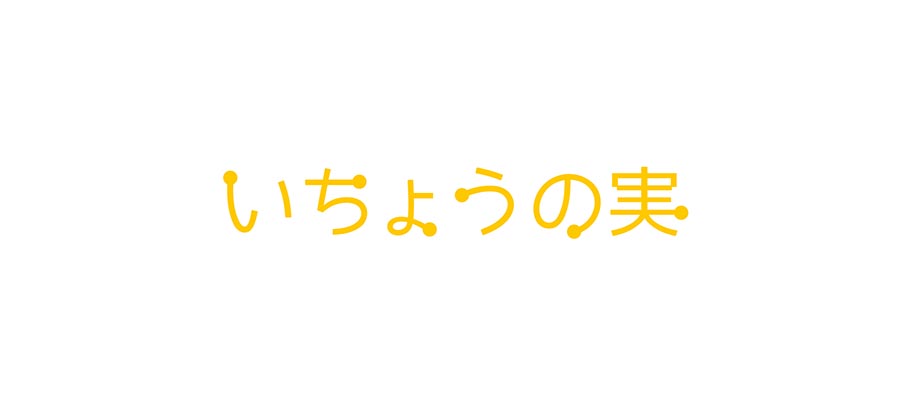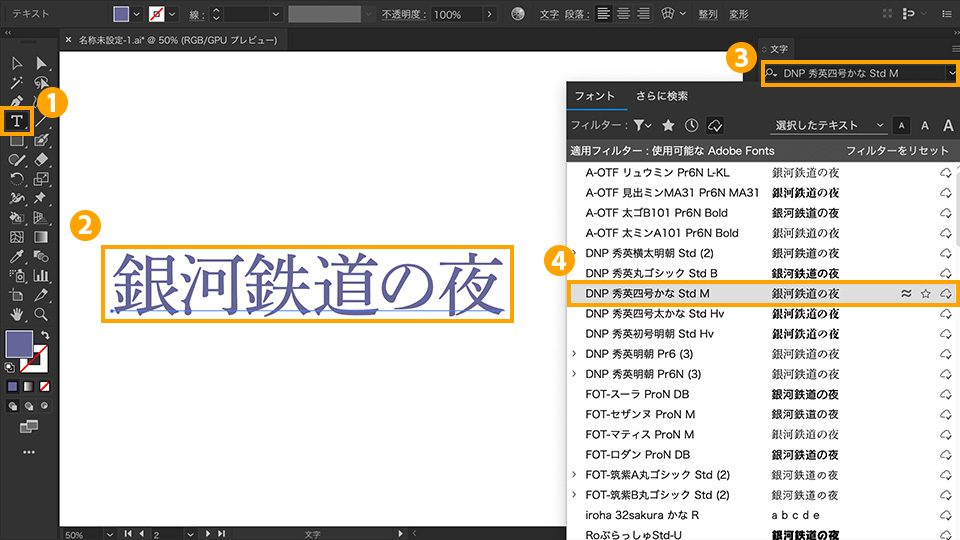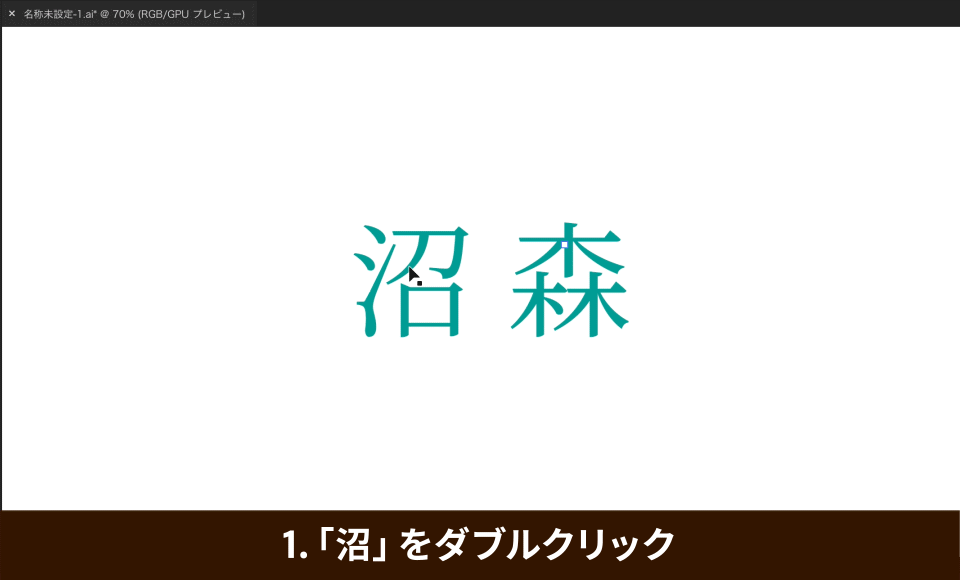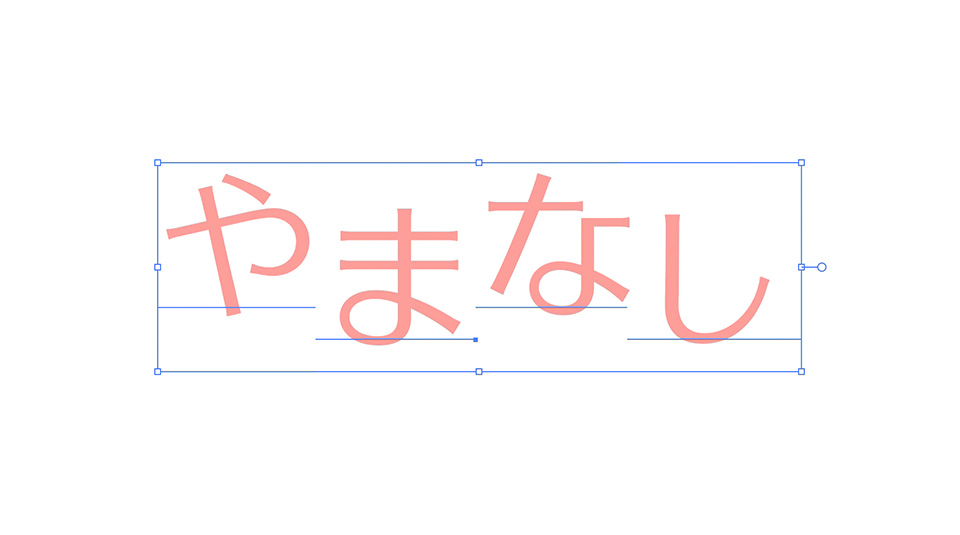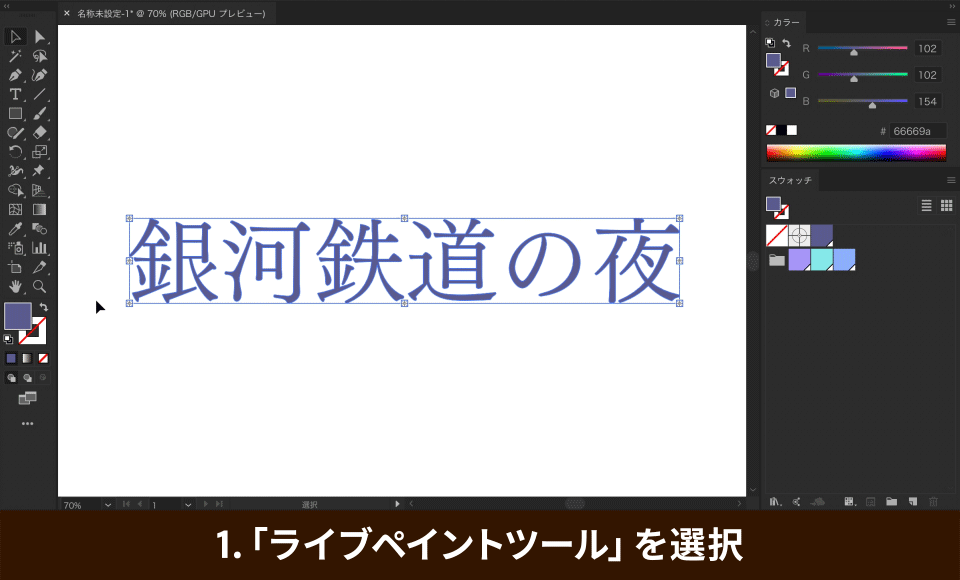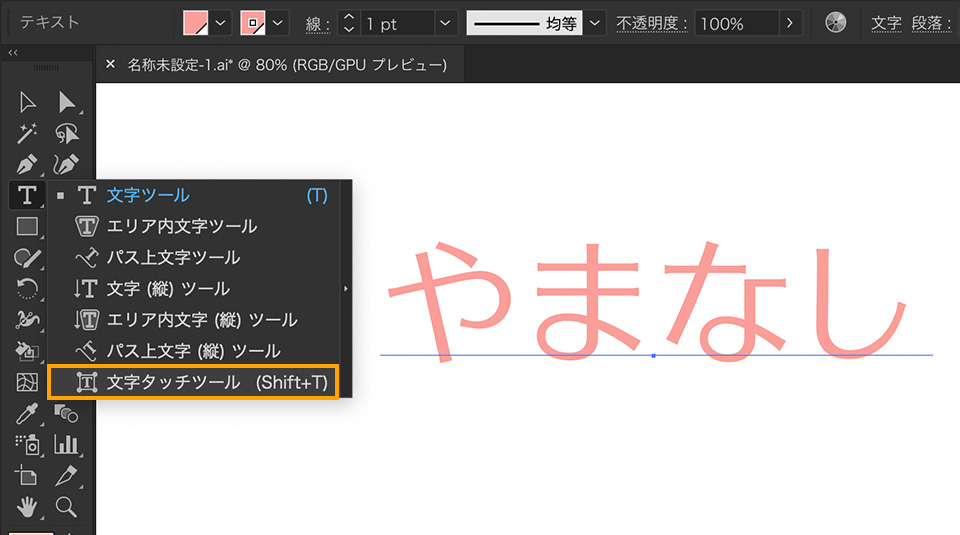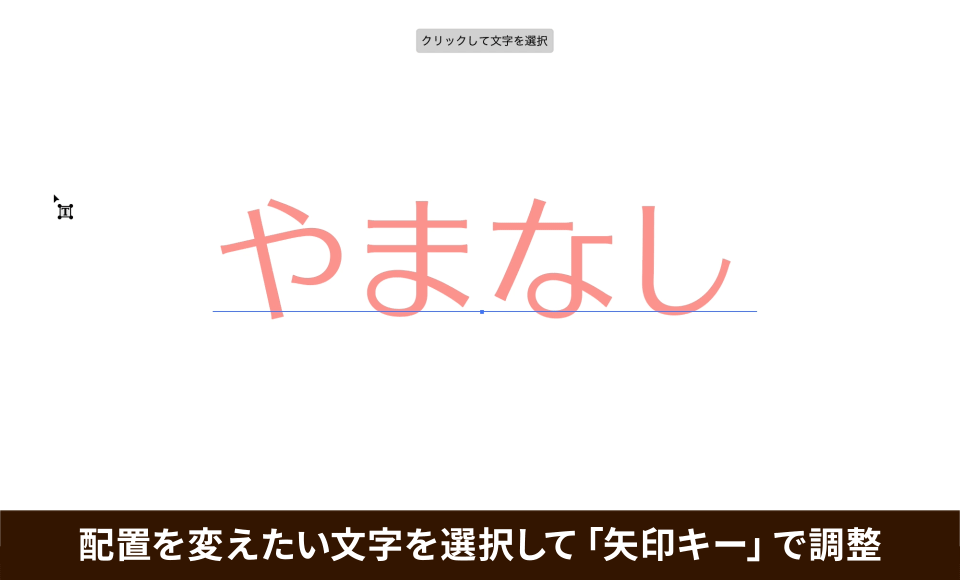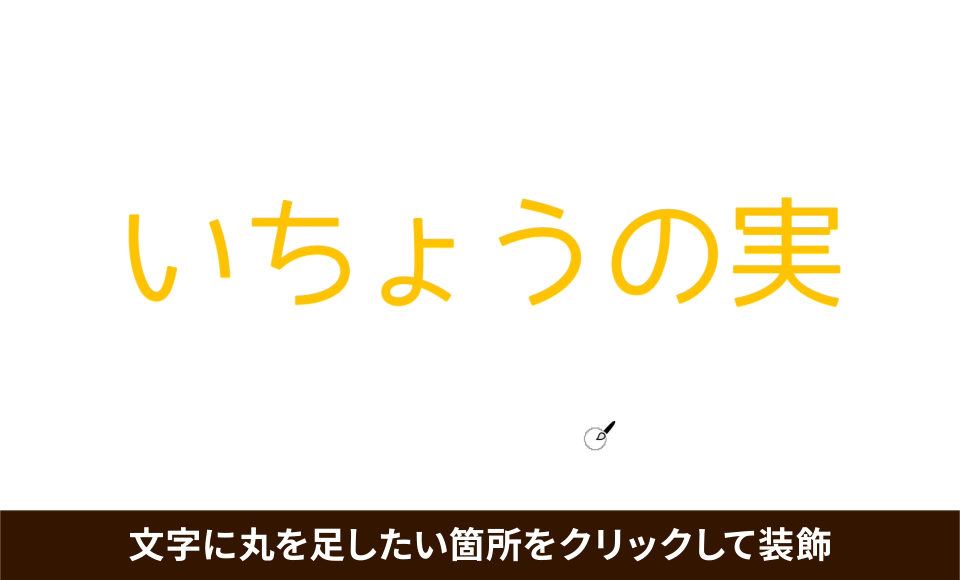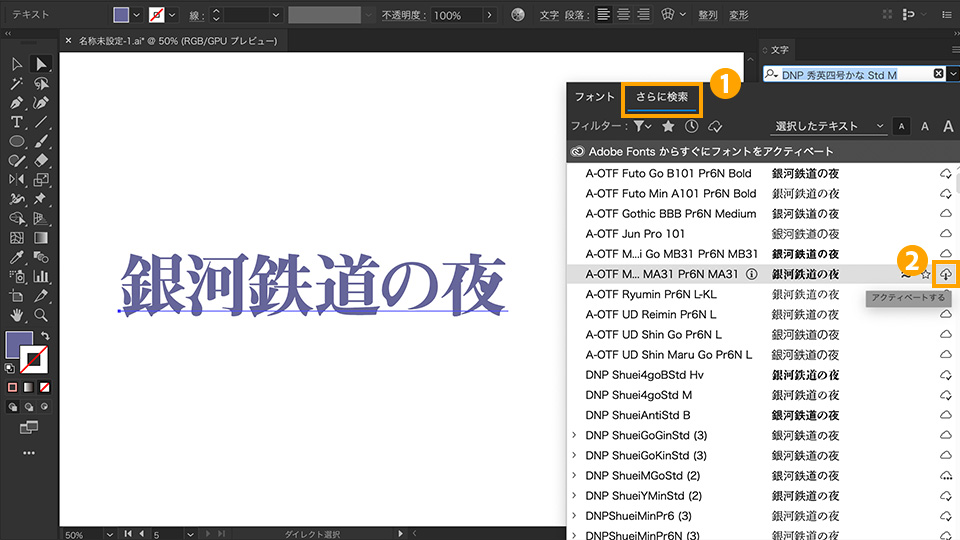
目を引くタイトル・ロゴデザインの方法:初級編
日本語のタイトルやロゴをデザインするときにヒントとなりそうなアイデアと作り方を6個紹介します。いつものフォントで入力した文字にひと手間加えて、楽しくてインパクトのあるタイトル文字を作りましょう
1. マドの中を塗る
1-1.
「文字ツール(T)」①を選択し、アートボード上をクリックして「銀河鉄道の夜」というテキストを作成します②。
1-2.
入力した文字を選択した状態で、「文字パネル」(ウインドウ → 書式 → 文字)を開きます。検索ボックス⓷の右にある「v」をクリックし、プルダウンのフォントメニュー④から使用したいフォントを選びます。
ヒント:
1-3.
文字を個別のオブジェクトとして編集するため、パスデータに変換します。これをアウトライン化と言います。「選択ツール」で文字を選択し、「書式 」→ 「アウトラインを作成」をクリックします。
文字をアウトライン化すると、テキスト情報が破棄されるため、フォントの変更や文字の打ち替えはできなくなります。
1-4.
続いて、文字のマドに色を追加していきますが、まず使用するカラーをスウォッチとして登録します。「スウォッチパネル」(ウインドウ → スウォッチ)を開き、下部の「新規スウォッチ」ボタンをクリックします。「新規スウォッチ」パネルが開くので、数値を入力してカラーを指定し、「OK」をクリックします。カラーがスウォッチパネルに追加されたら、同じ手順で計3つのカラースウォッチを作成します。
作成した3つカラースウォッチをすべて選択し、パネル下部の「新規カラーグループ」ボタンをクリックします。名前を入力し、「OK」をクリックします。スウォッチパネルに3つのカラーを含むカラーグループが追加されました。
1-5.
アウトラインテキストを選択した状態で、「オブジェクト」→「ライブペイント」→「作成」をクリックします。これでアウトラインテキストが、ライブペイントグループに変換されました。
1-6.
「ライブペイントツール(K)」を選択し、スウォッチパネルに追加したカラーグループを選択します。カーソル上に3つのカラーが表示され、中央に表示されているカラーが現在選択されているカラーになります。キーボードの矢印キー「←」「→」を押すと、別のカラーに切り替えることができます。
文字のマドの部分にカーソルを置くと、マドの内側が赤い線で囲まれるので、クリックすると選択されているカラーが適用されます。好みのカラーに切り替えながら、文字のマドに着色していきます。
2. 混植する
2-1.
「文字ツール(T)」を選択し、アートボード上をクリックして「春と修羅」というテキストを作成します。
2-2.
次に「文字タッチツール(Shift+T)」に切り替えます。文字タッチツールを使用すると、テキストを1文字ずつ選択し、フォントやサイズを変更したり、位置を移動したり回転したりすることができます。ここでは、「と」の文字を選択し、「文字パネル」から別のフォントを選んで適用します。
2-3.
今度は、バウンディングボックスのコーナーハンドルを内側方向にドラッグし、サイズを縮小します。縮小された分だけ、両隣の文字の空きが自動で詰まります。次に、「と」の文字を下方向にドラッグして移動し、他の文字とベースラインを揃えます。
3. 先端にモチーフをつける
3-1
「文字ツール(T)」を選択し、アートボード上をクリックして「いちょうの実」というテキストを作成します。作成したテキストを選択し、文字パネルから好みのフォントを選択します。
3-2.
テキストを選択した状態で、「書式 」→ 「アウトラインを作成」をクリックし、テキストをアウトライン化します。
3-3.
次に「塗りブラシツール(Shift+B)」①を選択し、ツールアイコンをダブルクリックしてオプションを表示します。ブラシのサイズ②を「20pt」に変更し、「OK」③をクリックします。
3-4.
文字の先端に丸を足して装飾していきます。塗りブラシツールで丸を足したい部分をクリックします。丸のサイズを変更したい時は、再度、塗りブラシツールのアイコンをダブルクリックしてオプションを表示するか、キーボードの「 [ 」「 ]」キーを押してブラシのサイズを変更することができます。好みの雰囲気になるまで調整してみましょう。
4. 斜体にする
4-1.
「文字ツール(T)」で「鳥の北斗七星」というテキストを作成し、好みのフォントを選択します。
4-2.
テキストを選択した状態で、「変形パネル」(ウインドウ → 変形)を開き、「シアー」①のプルダウンメニューから「10°」②を選択します。斜体がないフォントにも簡単に斜体効果をつけることができます。
5. 文字の要素をバラバラにする
5-1.
「文字ツール(T)」を選択し、アートボード上をクリックして「沼 森」というテキストを作成します。続いて、フォントを選択し、アウトラインを作成します。
※アウトラインの作成方法:
テキストを選択した状態で、「書式 」→ 「アウトラインを作成」をクリックし、テキストをアウトライン化します。
5-2.
「選択ツール(V)」でアウトラインテキストをダブルクリックすると、「編集モード」になります。さらに「沼」の文字をダブルクリックすると、文字の要素を個別に編集できるようになります。文字の要素をバラバラに移動してみましょう。この時、「沼」の文字以外は編集できない状態になります。
5-3.
「編集モード」を解除するには、アートボードの余白の部分をダブルクリックします。今度は、同様の操作で「森」の文字要素をバラバラにしてみましょう。
6. 配置を工夫する
6-1.
「文字ツール(T)」を選択し、アートボード上をクリックして「やまなし」というテキストを作成します。文字パネルからフォントを選択したら、ツールパネルで「文字タッチツール(Shift + T)」に切り替えます。
6-2.
配置を変えたい文字、ここでは「や」と「な」をそれぞれ選択して上に移動させます。キーボードの「↑」「↓」を使うと、左右にずれることなくキレイに配置できます。
6-3.
文字タッチツールは、文字の移動だけではなく回転やサイズの変更なども直感的に行えますので、文字表現の幅が格段に広がります。
また「文字タッチツール」で作成したものは、Illustratorの下位バージョンでもベースラインシフトなどの設定を保持しているため、アウトライン化して保存し直す必要はありません。
いかがでしたか、普段は入力するだけだった文字もIllustratorにあるさまざまなツールを利用すれば、1からデザインすることなく、インパクトのあるタイトル文字をデザインすることができます 。